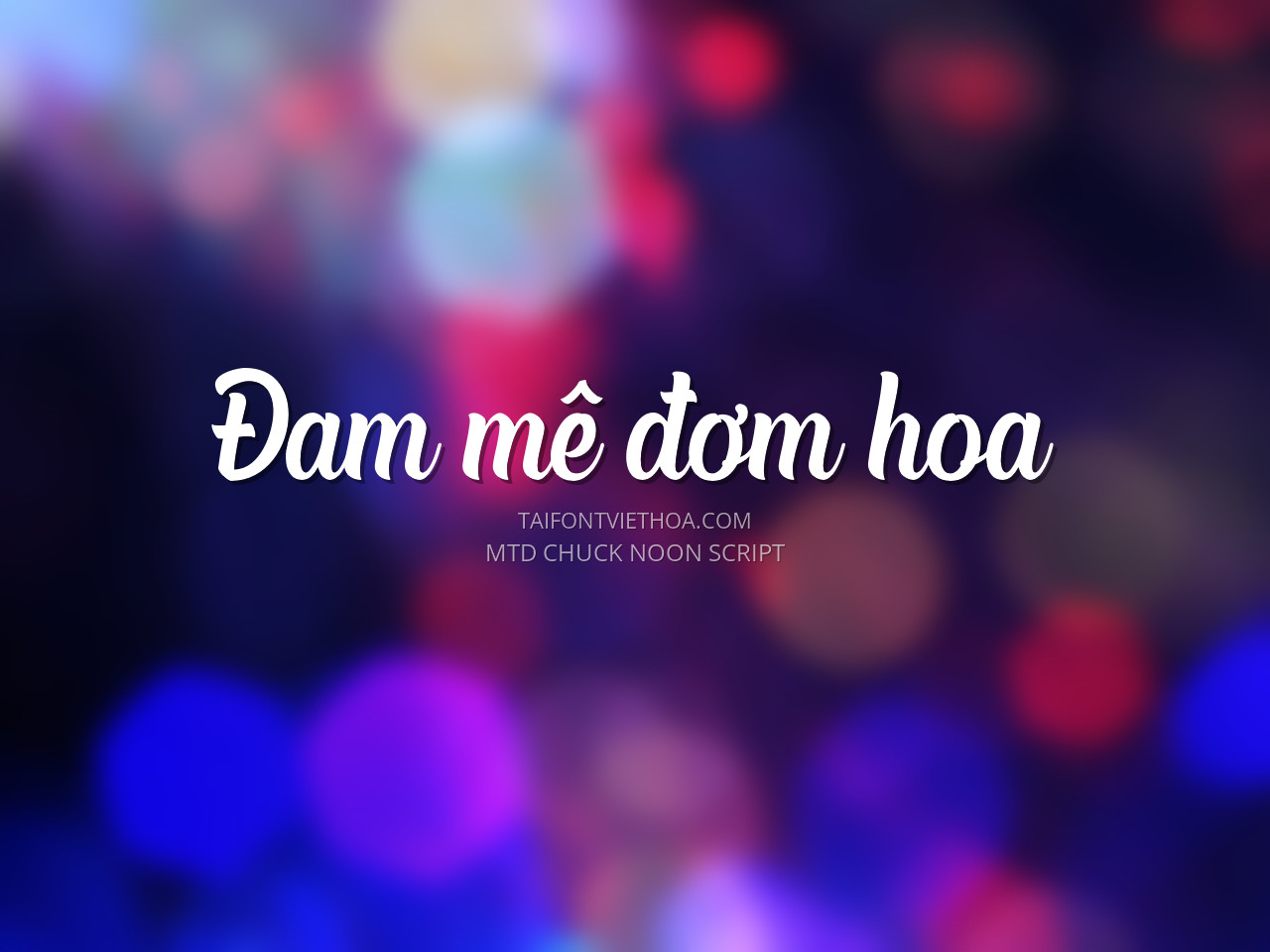
Giới thiệu về font Chuck Noon Script – Vẻ đẹp hoài cổ từ những nét bút tay mềm mại
Chuck Noon Script là một kiểu font chữ viết tay đậm chất hoài niệm, mang theo tinh thần thư pháp hiện đại xen lẫn phong cách retro Mỹ thập niên 60–70. Font này được phát hành dưới dạng thương mại trên các nền tảng như Creative Market, MyFonts, nhưng không công bố rõ tên tác giả. Với phong cách uyển chuyển và phóng khoáng, Chuck Noon Script nhanh chóng thu hút sự chú ý từ cộng đồng thiết kế quốc tế nhờ khả năng truyền tải cảm xúc và cá tính mạnh mẽ qua từng con chữ.
Phiên bản Việt hóa do Mộc Hạthực hiện đã bổ sung trọn bộ ký tự tiếng Việt, đảm bảo trải nghiệm gõ và thiết kế mượt mà trên mọi nền tảng từ Canva, Figma đến Adobe. Font hiện hỗ trợ hơn 50 ngôn ngữ với bộ glyph phong phú. Taifontviethoa.comđã sưu tầm và giới thiệu Chuck Noon Script như một lựa chọn đáng giá dành cho các nhà thiết kế yêu thích phong cách thư pháp hiện đại pha lẫn nét cổ điển, phù hợp với nhiều dự án cá nhân hóa, thương hiệu nghệ thuật và truyền thông cảm xúc.
Phong cách thiết kế nghệ thuật và các ứng dụng phù hợp của Chuck Noon Script
Font Chuck Noon Script mang đường nét mềm mại, hơi nghiêng nhẹ với độ tương phản giữa các nét được kiểm soát chặt chẽ. Các ký tự liên kết mạch lạc với nhau, tạo cảm giác như những nét bút lông được viết tay liền mạch. Font cũng bao gồm các ký tự thay thế (alternates), ligatures và swashes – cho phép tạo ra những kiểu trình bày chữ độc đáo, cá nhân hóa cao.
Chuck Noon Script là lựa chọn hoàn hảo cho các thiết kế thiệp cưới, chữ ký cá nhân, logo thương hiệu cao cấp, tiêu đề bài viết, nhãn mỹ phẩm thủ công hoặc các poster cổ điển. Font này đặc biệt phù hợp với các ngành nghề như tổ chức sự kiện, ngành cưới hỏi, spa – làm đẹp, sản phẩm nghệ thuật thủ công, hoặc các thương hiệu cần tạo dựng hình ảnh cảm xúc và độc đáo.